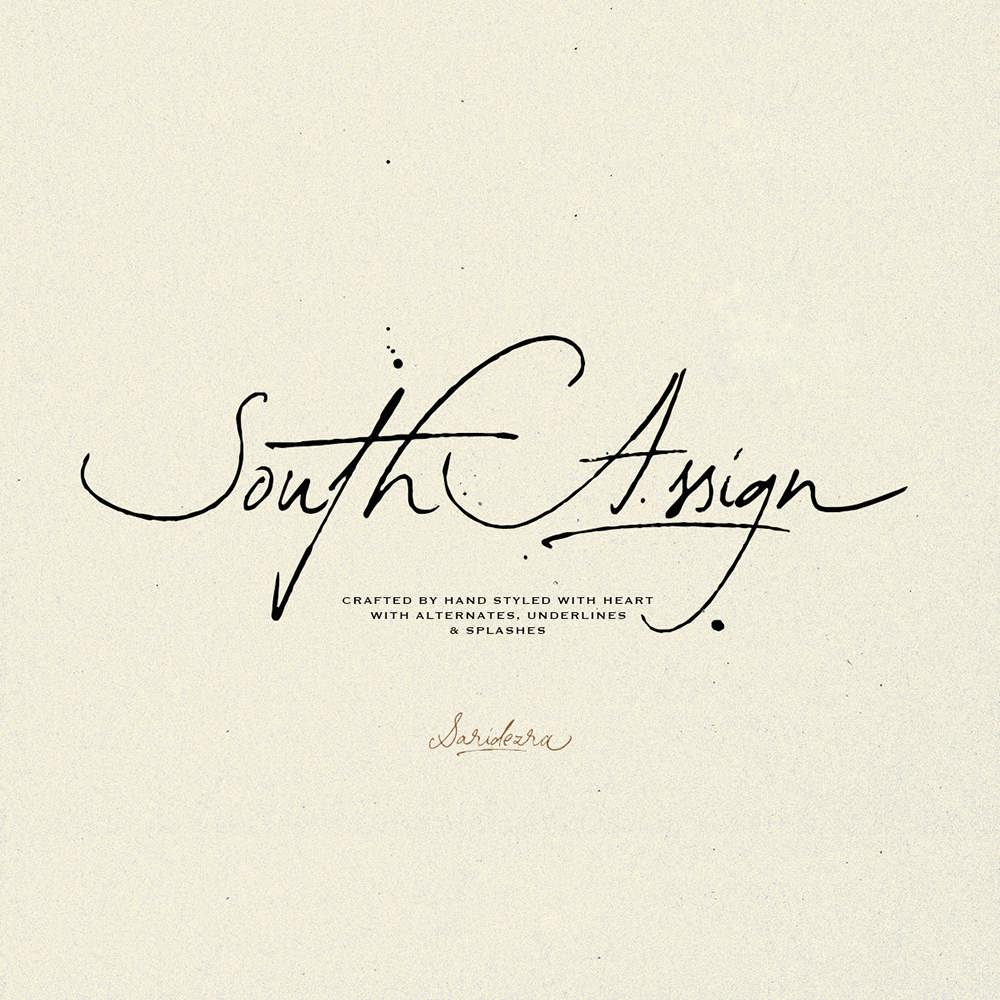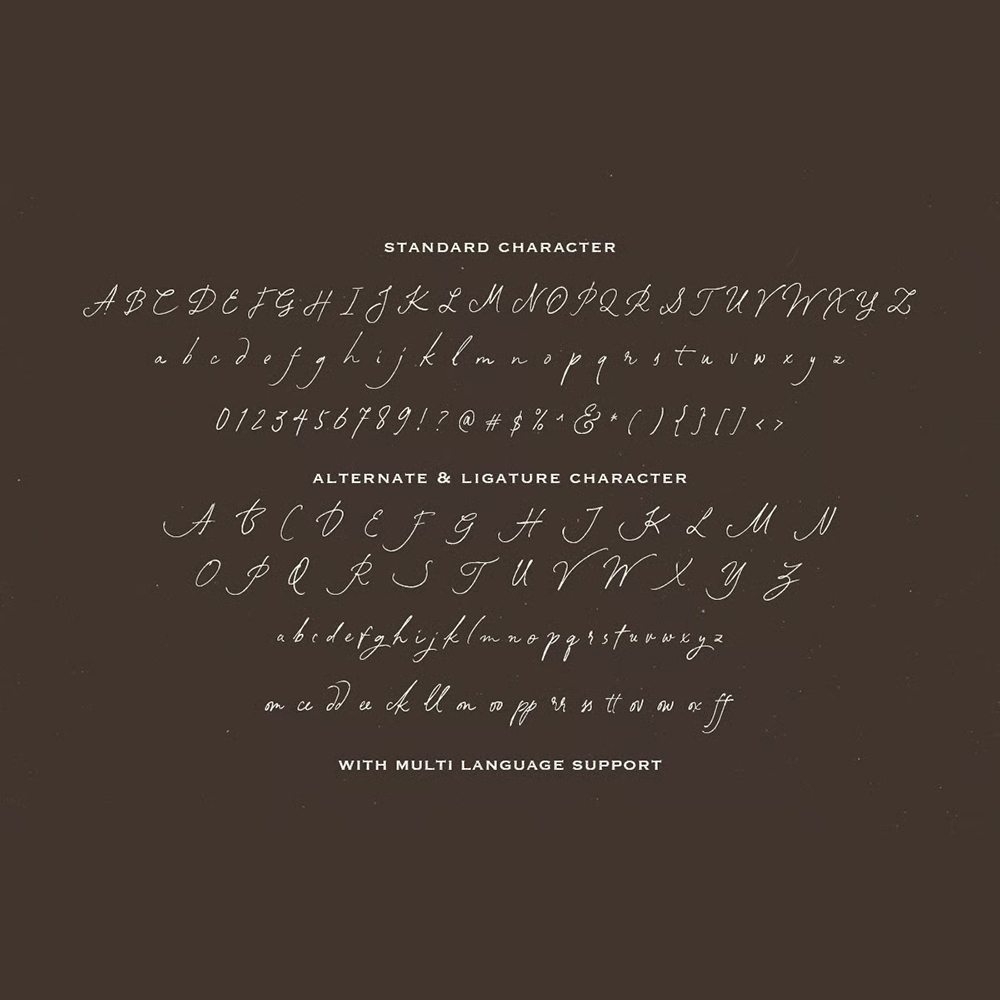
فونت پرمیوم و انگلیسی South Assign الهام از سبک قدیمی است که ویژگیهای زیادی دارد. این فونت دارای جایگزینها، زیرخطها و لکههایی است که میتوانید از طریق ویژگیهای OpenType به آنها دسترسی داشته باشید. میتوانید از این فونت برای هر منظوری مانند برندسازی، نقل قولها، امضا و به خصوص کارتهای دعوت عروسی استفاده کنید.